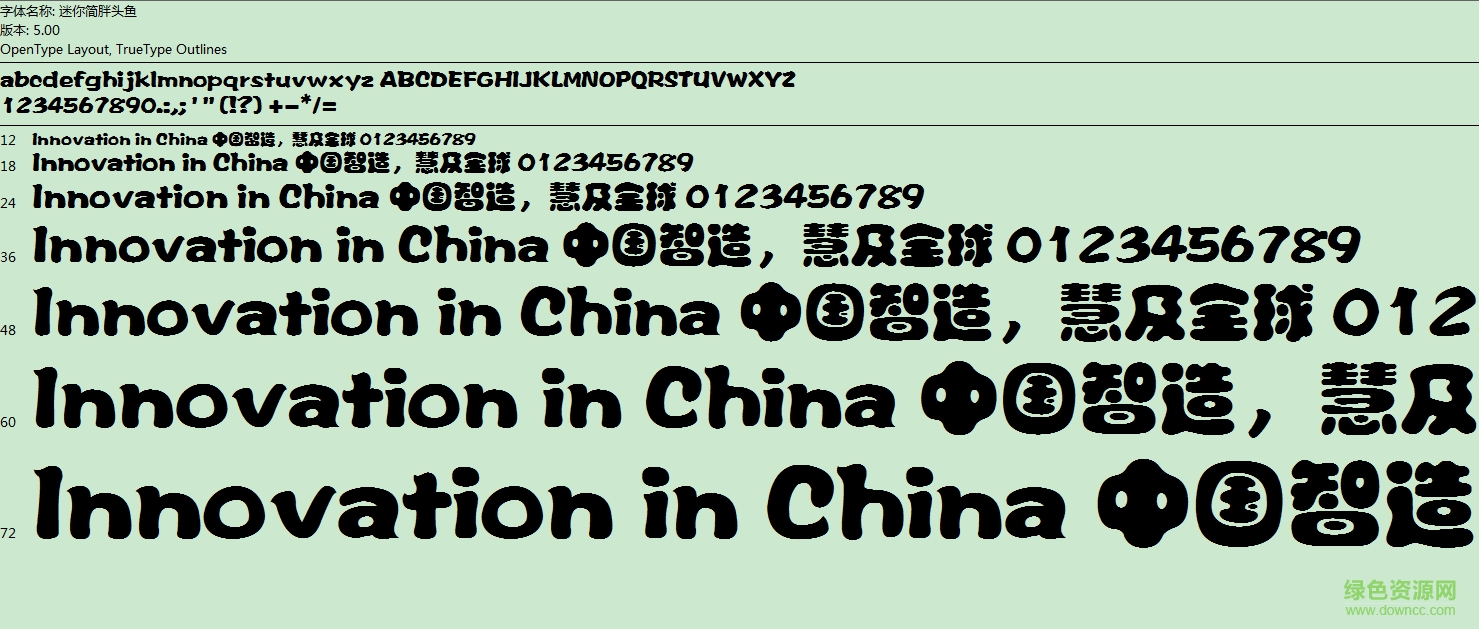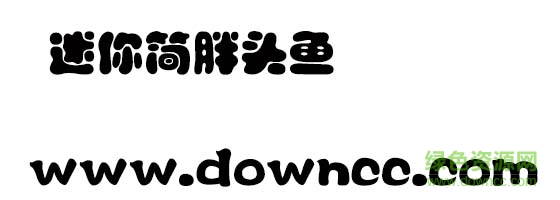
迷你簡(jiǎn)胖頭魚(yú)是一款非??蓯?ài)的一款迷你字體,字體看起來(lái)厚實(shí)粗重,非常適用于廣告設(shè)計(jì)等方面,喜歡的朋友快來(lái)綠色資源網(wǎng)踴躍下載吧!
迷你簡(jiǎn)胖頭魚(yú)是一款厚實(shí)粗重的字體,能夠突出重點(diǎn),適用于廣告設(shè)計(jì),標(biāo)題設(shè)計(jì)等